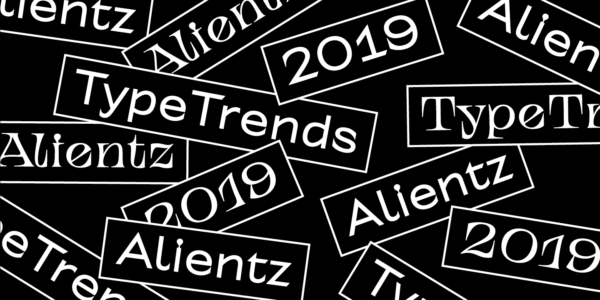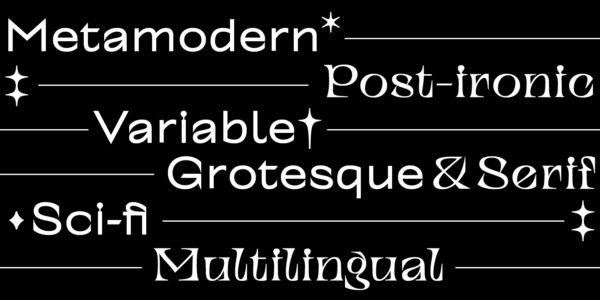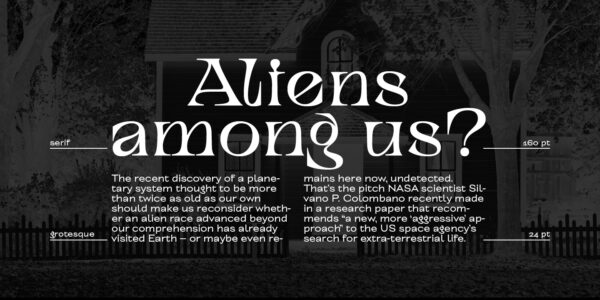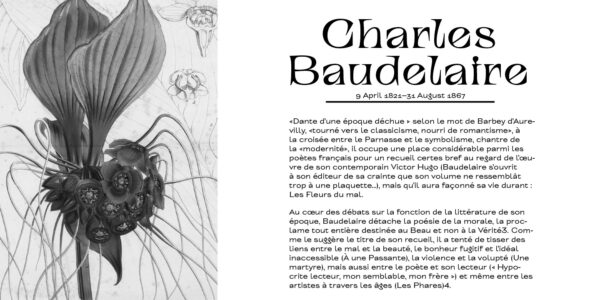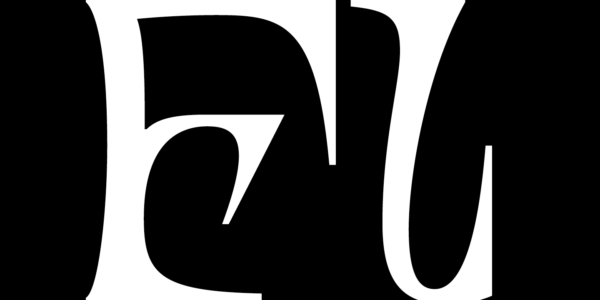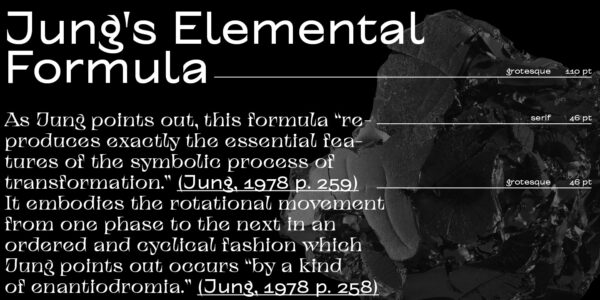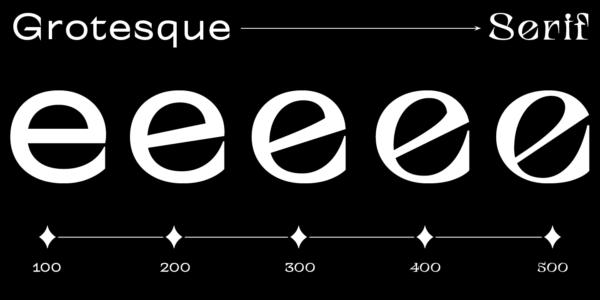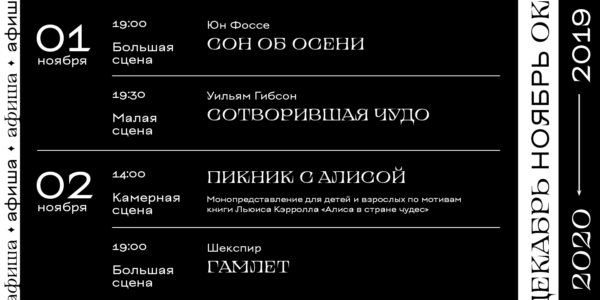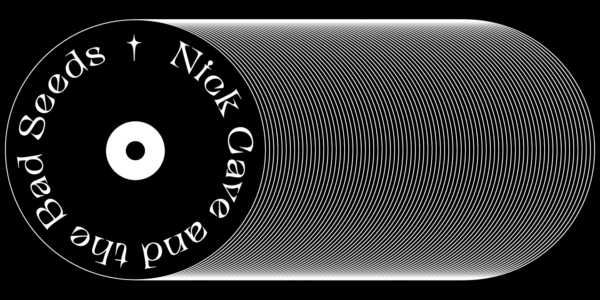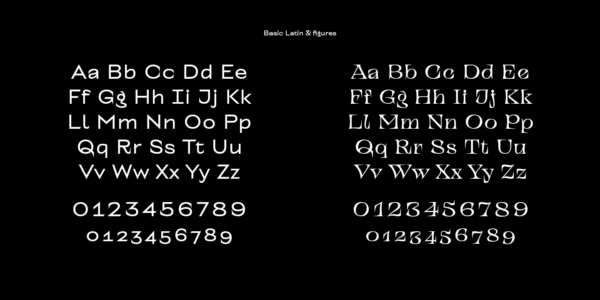
TT Alientz
TT Alientz — ТТ Элиенц
Произносится «ТТ Элиенц». «Alientz» — производное слово от Alien, в переводе с английского «пришелец». Буквы «TT» являются аббревиатурой названия компании.
TT Alientz — вариативный шрифт, способный меняться от лаконичного инопланетного гротеска до сверхакцидентной и очень колючей антиквы.
TT Alientz
От инопланетного гротеска — к сверх-акцидентной колючей антикве
TT Alientz
Семейство Alientz состоит из 3 шрифтов: гротеск, антиква и вариативный шрифт. В состав каждого шрифта входит более 470 глифов.Вариативность в шрифте влияет на изменение общей стилистики шрифта — двигая ползунок регулировки вариативной оси вы можете пройти путь от лаконичного гротеска до экстремальной антиквы.
О гарнитуре TT Alientz
TT Alientz является вариативным шрифтом, который позволяет пользователю совершить визуальное путешествие от лаконичного инопланетного гротеска к сверх акцидентной и очень колючей антикве. В рамках этого проекта мы решили исследовать влияние чужеродной субстанции и дальнейшую трансформацию исходных форм, которая в конце концов приводит к экстремальным визуальным изменениям.
Семейство Alientz состоит из 3 шрифтов: гротеск, антиква и вариативный шрифт. В состав каждого шрифта входит более 470 глифов. Кроме широкой языковой поддержки (включая Кириллицу), в шрифте есть стильные лигатуры, контекстуальные альтернейты, старостильные цифры. Вариативность в шрифте влияет на изменение общей стилистики шрифта — двигая ползунок регулировки вариативной оси вы можете пройти путь от лаконичного гротеска до экстремальной антиквы.
TT Alientz Grotesque это достаточно лаконичный хипстерский гротеск, но со своими небольшими особенностями. В дизайне некоторых букв гротеска можно обнаружить небольшие острые элементы, которые добавляют уникальности и характера шрифту, при использовании его в крупных надписях и заголовках. При этом, когда вы используете шрифт в маленьких размерах кегля и в текстовых блоках, острые элементы не сильно влияют на его читаемость. Дизайн некоторых букв гротеска достаточно своеобразен и призван подчеркнуть первоначальную концепцию легкой инопланетности.
TT Alientz Serif — это инфицированный TT Alientz Grotesque и результат его изменений. В отличии от гротеска антиква динамичная, тягучая, пластичная и очень колючая. В антикве много плавных линий и не совсем стандартный контраст у штрихов. Можно отметить, что большинство засечек в антикве нацелены внутрь, а не наружу. Несмотря на свою экстремальность, антиква будет хорошо смотреться как в больших размерах, так и в небольших кеглях.
Basic Latin Basic Cyrillic Extended Latin Stylistic Alternates, Standard and Discretionary Ligatures|salt,liga,dlig Lining Figures, Currencies Old-style Figures|onum Punctuation, Symbols, Mathematical Symbols, Arrows
liga | Standard Ligatures
ff fi ffj
onum | Oldstyle Figures
1638
case | Case Sensitive Forms
({[H]})
calt | Contextual Alternates
ft fi